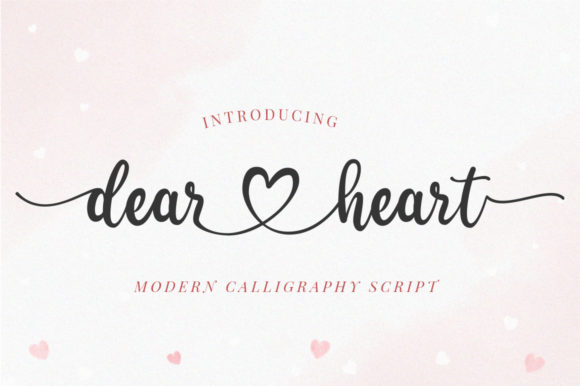
Dear Heart - это романтический рукописный шрифт.
Идеально подходит для написания писем или приглашений на День Святого Валентина, этот шрифт, несомненно, поднимет ваш дизайн.